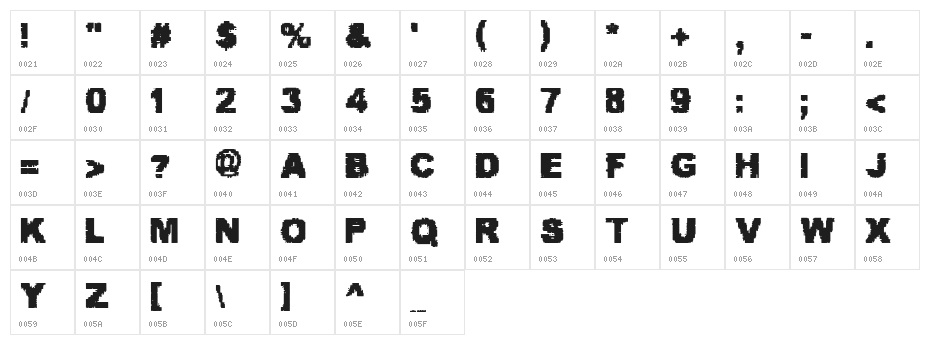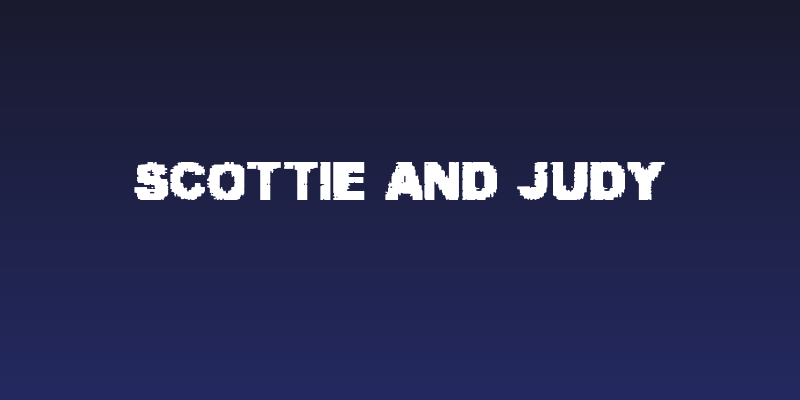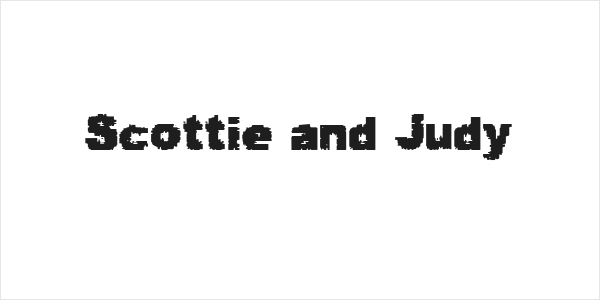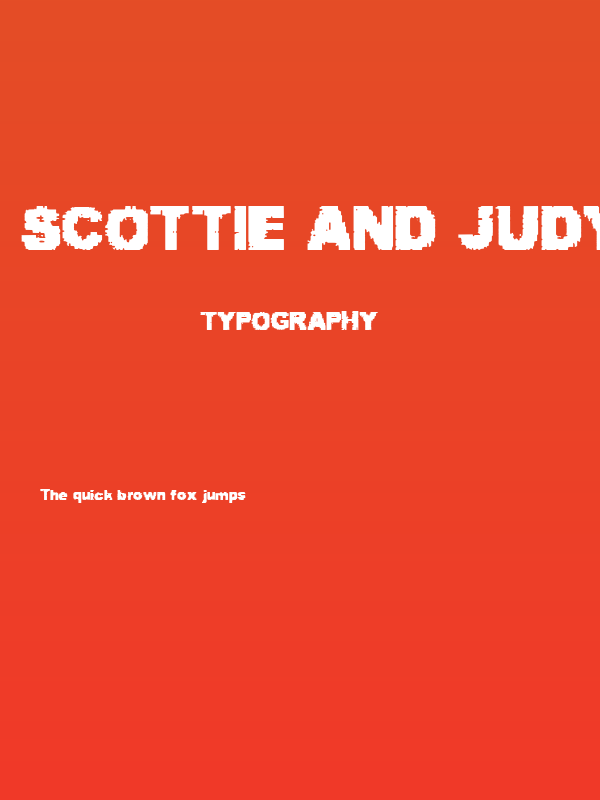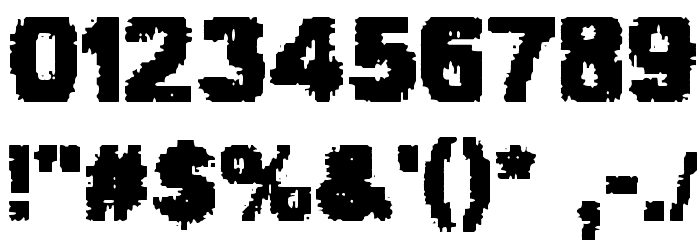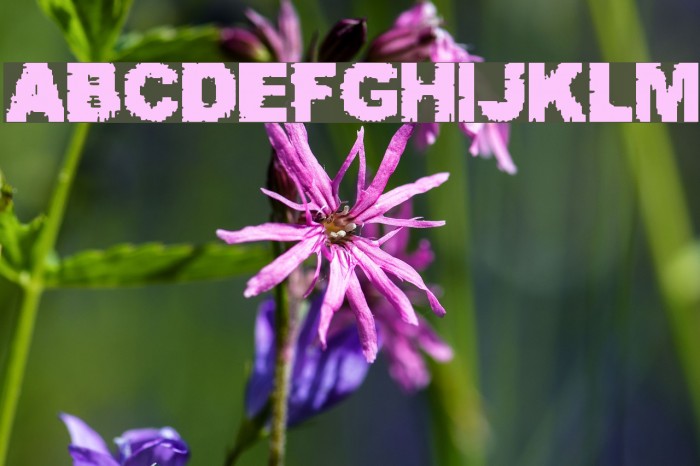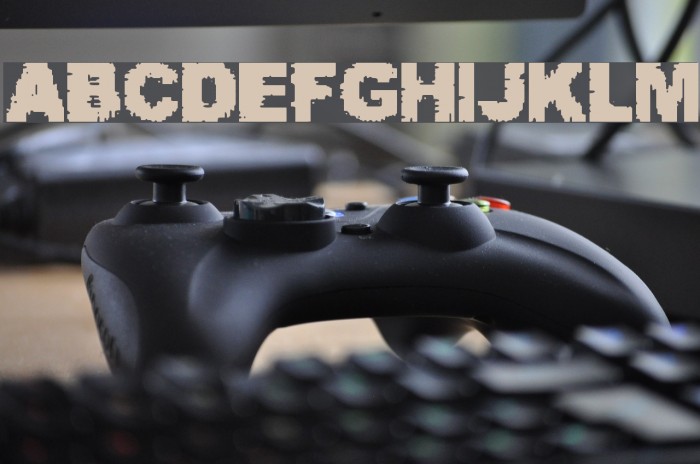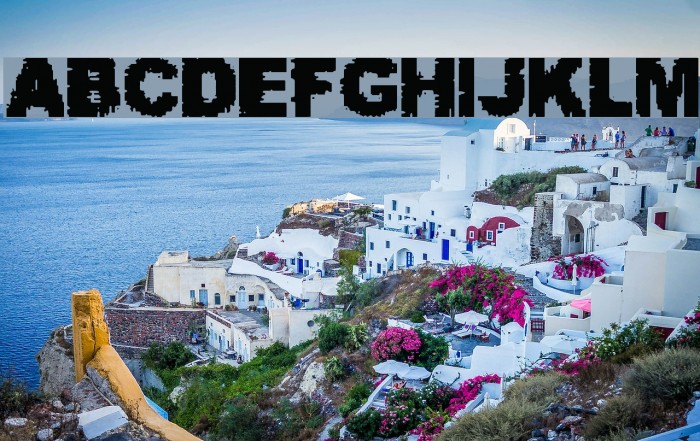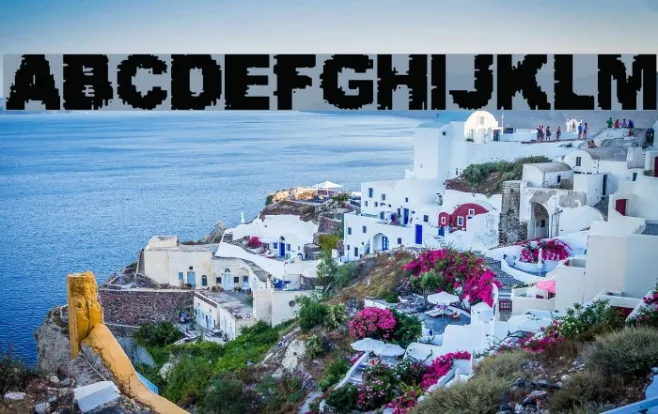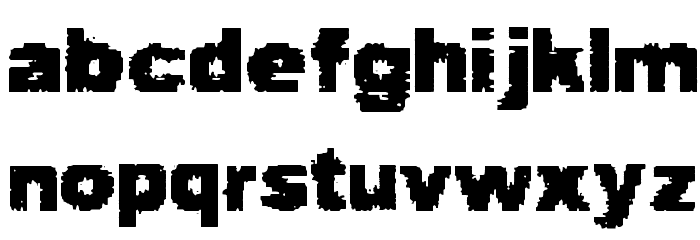
Scottie and Judy Font
| Gesamtstil | Vintage |
| Vorgeschlagene Projekte | Ideal for posters, album covers, branding for edgy products, or any design needing a vintage or grunge aesthetic. |